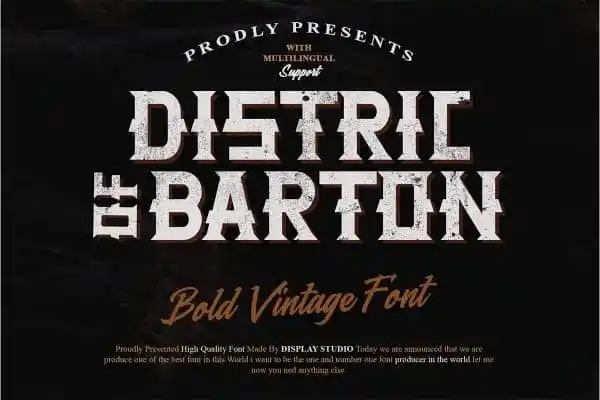
Distric of Barthon Display Font – Fonte Grátis
Distric of Barthon Display Font
A Distric of Barthon Display Font é uma elegante e moderna fonte para uso expositivo criada para projetos de marca, logomarca, anúncios, embalagens, publicidade, etiquetas, fotos, invitations, cartões-postais, selos e até mesmo camisetas. Ideal para trabalhos que exigem um visual atraente e único em mídias sociais e materiais impressos, este fonte é perfeita para definir sua identidade visual de maneira sofisticada e contemporânea. Com uma aparência cuidadosamente elaborada com detalhes meticulosamente construídos à mão, esta fonte oferece um amplo espectro de personalização para atender a todos os seus projetos. Seja em um layout de marca impactante ou em um recado rápido e direto no Instagram Stories, Distric of Barthon Display Font é uma opção confiável para criar um visual que se destaca entre a multidão. Esta fonte traz consigo a liberdade criativa que você precisa para expressar sua personalidade de maneira única e eficaz. Suas linhas fortes, texturas detalhadas e ricos tons coloridos permitem uma ampla gama de possibilidades, desde anúncios poderosos até cartões-postais delicados. Na era da interatividade digital, a Distric of Barthon Display Font se destaca como um recurso essencial para qualquer designer gráfico. Não importa o tamanho ou o formato do seu projeto, este fonte mantém sua versatilidade e originalidade, sempre proporcionando resultados impressionantes e memoráveis.